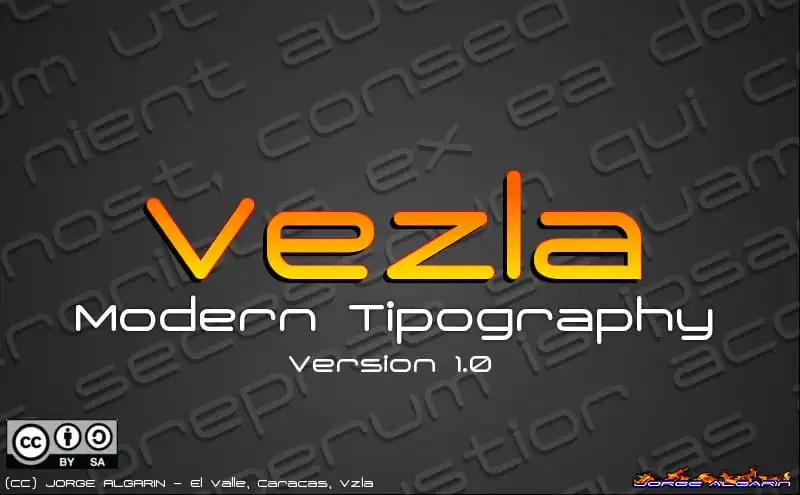
Vezla Sans Serif Font – Download Grátis
Vezla Sans Serif é uma família de fontes inspirada no tipo moderno monolíneo, criada pelo designer Jorge Algarin. Essa fonte traz características futuristas e um ar “tumblr” à sua aparição, equilibrando elementos modernos e modernamente futuristas em seu design único. Esta família de fontes é perfeita para uso em materiais como flyers, cartazes, etiquetas de camisa ou qualquer outra exigência de design que você queira tornar incrível. Ideal para uma variedade de aplicações gráficas, Vezla Sans Serif oferece um toque único e moderno sem perder a elegância necessária em projetos profissionais. Comprar essa fonte é garantir um toque inovador em qualquer projeto visual que você estiver criando.